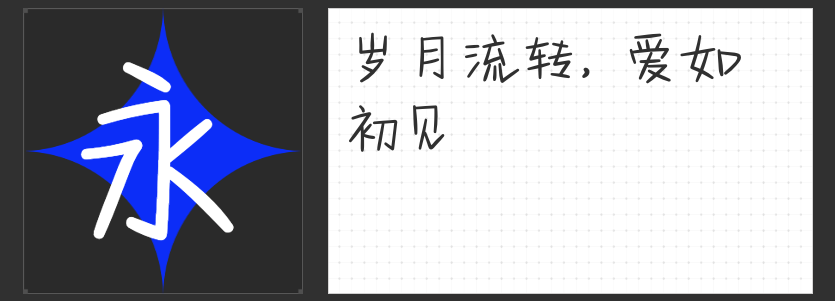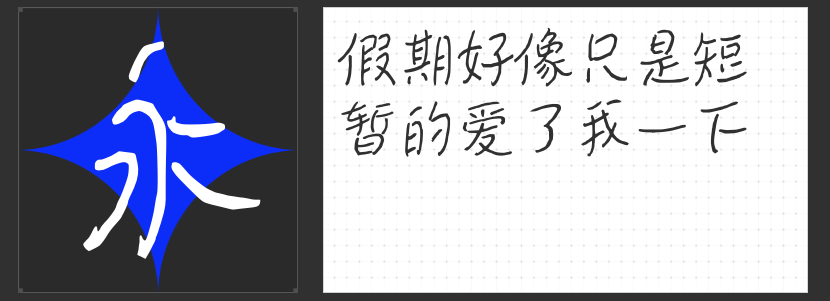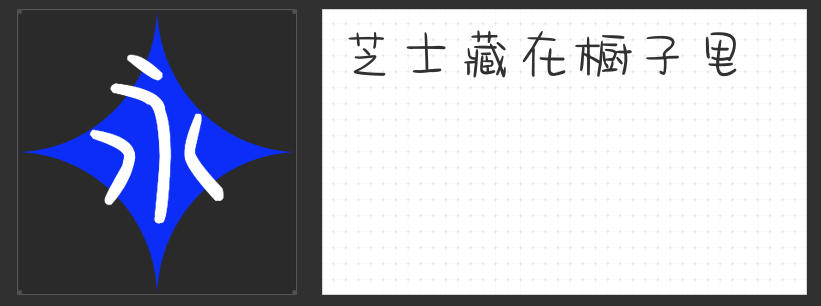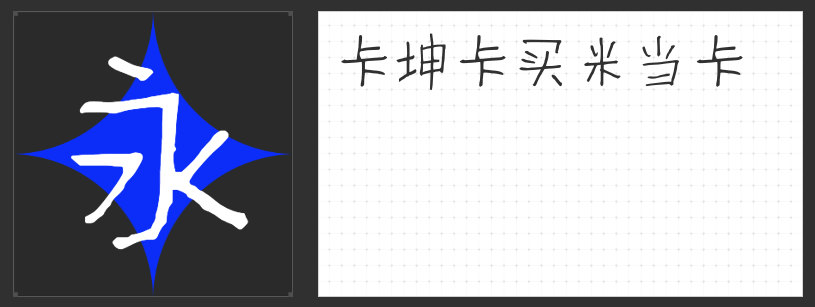
设计中的温柔力量:四款治愈系可爱字体推荐
在视觉设计中,字体的选择往往决定了作品的情感基调。当需要传递温暖、灵动或青春气息时,一款恰到好处的可爱字体能瞬间拉近与观者的距离。以下四款风格各异的可爱字体,以独特的笔触与结构为设计注入鲜活生命力,满足多元场景的创意需求。
一、贴仔初恋体
这款手写字体如同从青春日记中跃然而出,笔画俏皮中带着工整的克制感,仿佛少女用铅笔在信纸上认真书写的模样。起笔收尾的微小弧度与均匀的字间距,既保留了手写的自然呼吸感,又避免了过度随意带来的凌乱。其适中的粗细与清晰的字形,让文字在保持可爱特质的同时,仍具备优秀的可读性,适合需要平衡趣味性与专业感的场景。
二、MyFont求假期简 细体
以学生时代作业本字体为灵感,这款细体通过圆润的笔画与无装饰的简洁结构,唤起纯真年代的集体记忆。纤细的线条如同用圆珠笔轻轻勾勒,转折处自然柔化,赋予文字棉花糖般的轻盈质感。极高的识别度与低调的可爱感,使其成为需要大量文字排版时的理想选择,既能营造亲切氛围,又不会因过度设计分散注意力。
三、MyFont萨瓦迪卡简 细体
这款字体以张弛有度的连笔与清丽结体构建独特韵律,直线与弧线的巧妙交织,让文字如舞蹈般灵动。细体设计在保持阅读流畅性的同时,通过笔画的轻重变化传递出克制的高级感。其风格既适合长文本的沉浸式阅读,也能作为标题点缀,为设计增添一抹东方美学的含蓄诗意。
四、字圈也字杰瑞手迹
作为硬笔手写体的代表,字圈杰瑞手迹以秀丽颀长的字形与纤细流畅的笔触,展现出书写者从容自信的气质。主笔的突出延伸与收放的微妙处理,让每个字都如独立艺术品般耐人寻味。细腻的线条中暗藏力度变化,方圆结合的结构既保留传统书法的韵味,又符合现代审美,为设计注入优雅而不失活力的视觉张力。
这四款字体以不同方式诠释可爱的多重维度,从青涩懵懂到优雅从容,为设计师提供丰富的情感表达工具。无论是品牌包装、海报标题还是数字界面,它们都能以温柔笔触唤醒观者心底的柔软角落。